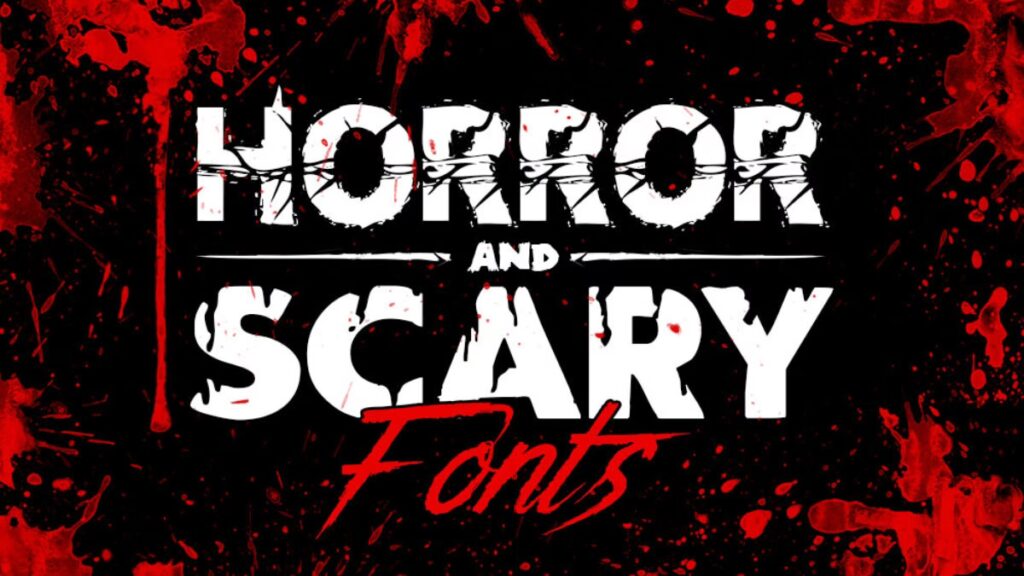
Typografi er et kraftfuldt værktøj i design, og når målet er at vække følelser af frygt, mystik eller ubehag, er valget af skrifttype afgørende. Skræmmende skrifttyper kan forvandle en almindelig plakat til et mareridtbrændstof eller give et logo en dyster, urovækkende kant, der passer perfekt til horror- eller Halloween-temaer. De er et must-have i værktøjskassen for enhver designer eller fotograf, der arbejder med mørke eller uhyggelige koncepter.
Disse skrifttyper er mere end bare bogstaver; de er visuelle elementer, der fortæller en historie, før du overhovedet læser ordene. De kan simulere dryppende blod, gamle, forvitrede inskriptioner, forvredne former, der antyder galskab, eller skarpe, takkede kanter, der skriger fare. At forstå, hvad der gør en skrifttype skræmmende, og hvordan man bedst anvender dem, er nøglen til at skabe virkelig mindeværdige og effektive designs.
Hvad Gør En Skrifttype Skræmmende?
En skræmmende skrifttype er designet til at fremkalde specifikke følelser og associationer relateret til frygt, horror, mystik eller det overnaturlige. Disse følelser opnås gennem forskellige visuelle karakteristika. Ofte ser man skrifttyper med takkede kanter, der ligner revner, kløer eller brudte overflader. Disse uregelmæssigheder skaber en følelse af fare, vold eller forfald.
En anden populær teknik er at simulere fysiske effekter som dryppende væske, mest almindeligt blod eller blæk. Skrifttyper med dryppende effekter er øjeblikkeligt forbundet med horror, kriminalitet eller uhygge. De kan se våde, klistrede og foruroligende ud, hvilket gør dem ideelle til titler eller overskrifter, hvor man ønsker en stærk, grafisk effekt.
Ru teksturer og forvitrede udseender er også effektive. En skrifttype, der ser ud som om den er ridset, plettet, eller ældet, kan give en følelse af historie, forladthed eller dæmonisk besættelse. Disse teksturer tilføjer dybde og realisme til det uhyggelige tema.
Forvredne eller forvrængede bogstavformer kan skabe en følelse af ustabilitet, galskab eller en verden ude af balance. Bogstaver, der ser ud til at smelte, sno sig, ryste eller falde fra hinanden, er dybt urovækkende og kan bruges til at repræsentere mentale forstyrrelser, overnaturlige kræfter eller et generelt tab af virkelighedssans. Kaotiske strøg og uregelmæssige former bidrager til denne fornemmelse af uorden og terror.
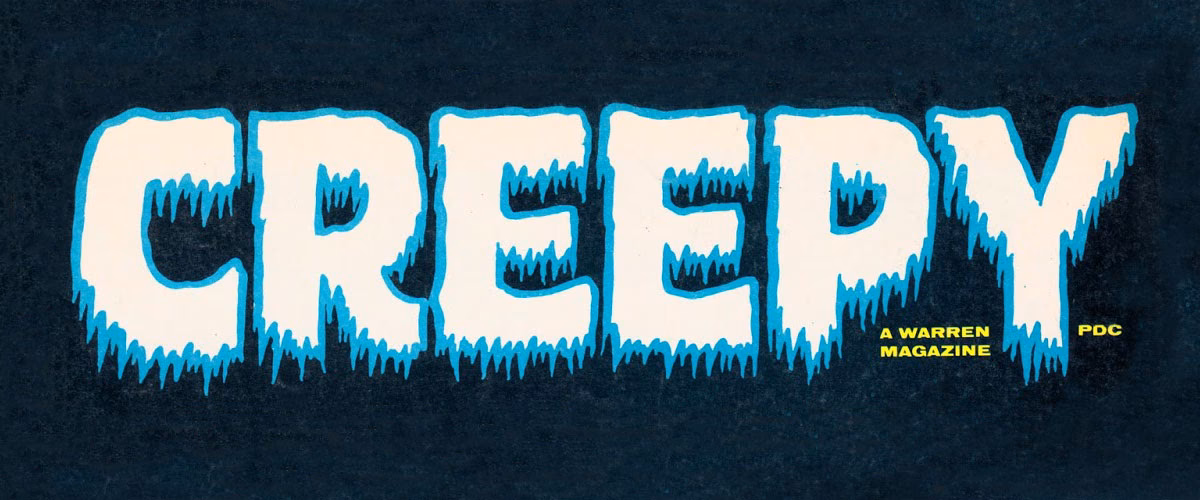
Endelig kan selv enkle, men tunge eller gotiske skrifttyper opfattes som skræmmende, især når de bruges i en passende kontekst. En fed, mørk, gotisk skrifttype kan give en følelse af gammel ondskab, okkultisme eller dysterhed, der fungerer godt til Halloween eller mere traditionelle horror-temaer.
Brug af Skræmmende Skrifttyper i Design og Fotografi
At vælge den rigtige skræmmende skrifttype er kun første skridt. Hvordan du bruger den, er lige så vigtigt for at maksimere effekten. Her er nogle tips til at bruge skræmmende skrifttyper effektivt i dine designs:
- Brug dem sparsomt: Skræmmende skrifttyper er ofte meget dekorative og kan være svære at læse i længere tekstblokke. De fungerer bedst til overskrifter, titler, logoer eller korte sætninger, hvor de kan fange opmærksomheden uden at trætte øjnene. Brug en mere læselig, men passende, skrifttype til brødtekst, hvis nødvendigt.
- Kombiner med passende baggrunde: Mørke, stemningsfulde baggrunde er ideelle til skræmmende skrifttyper. Overvej baggrunde med lav belysning, skygger, tåge, gamle teksturer (træ, mursten, rust) eller billeder, der passer til det uhyggelige tema.
- Tilføj teksturer og effekter: For at forstærke det skræmmende udseende kan du tilføje yderligere grafiske effekter til selve teksten eller dens omgivelser. Dette kan inkludere ridser, pletter, vignetter, lysglimt eller skygger, der får teksten til at se mere integreret ud i designet og mere fysisk tilstedeværende (og skræmmende!).
- Farvevalg er vigtigt: Farver som dyb rød (blod), sort (mørke, død), mørkegrå (skygger, aske) og knoglehvid (spøgelser, knogler) er klassiske valg til skræmmende typografi. Neonfarver som grøn eller lilla kan også bruges til at give et mere overnaturligt eller syret udtryk, især i kombination med mørke baggrunde.
- Tænk på konteksten: Hvilken specifik type horror eller uhygge repræsenterer dit design? En dryppende blodskrifttype passer måske til en slasherfilmplakat, mens en ældgammel, forvitret skrifttype er bedre til et okkult tema. Vælg en skrifttype, hvis stil matcher den specifikke historie eller følelse, du vil formidle.
Populære Stilarter og Eksempler fra Horror
Gennem tiden har visse skrifttypestilarter og endda specifikke skrifttyper opnået ikonisk status inden for horror. De er blevet synonyme med genren og genkendes øjeblikkeligt af fans.
En stil, der ofte ses, er en tung, gotisk-inspireret skrifttype med skarpe, spidse kanter. Denne stil kan føles både gammeldags og truende. Forestil dig en skrifttype, der ser ud som om den er ridset ind i sten eller hugget ud af mørkt træ – den udstråler en følelse af ældgammel ondskab.
En anden stil er den kaotiske, forvrængede skrifttype. Disse ser ud som om de er håndskrevne i panik, eller som om de er påvirket af en overnaturlig kraft. Bogstaverne kan have uregelmæssige størrelser, vinkler eller endda mangle dele. Denne stil er perfekt til at skabe en følelse af ustabilitet, galskab eller dæmonisk indflydelse.
Den dryppende stil, som nævnt tidligere, er også meget populær. Disse skrifttyper ser ud som om de er ved at smelte eller græde blod eller sort blæk. De er utroligt grafiske og vækker øjeblikkeligt associationer til vold, død og uhygge. En skrifttype beskrevet som havende en 'venomous' eller 'dødbringende' udseende falder ofte ind under denne kategori, med elementer der ligner hugtænder eller dryp.
Nogle skrifttyper er blevet berømte på grund af deres brug i ikoniske horrorproduktioner. For eksempel er skrifttypen ITC Serif Gothic ofte forbundet med horror, især efter dens brug i plakater og titler for film som 'Halloween'. Dens skarpe seriffer og tunge vægt giver den et både klassisk og ildevarslende udseende, der har gjort den til et populært valg inden for indie horror og mid-budget film i årtier.
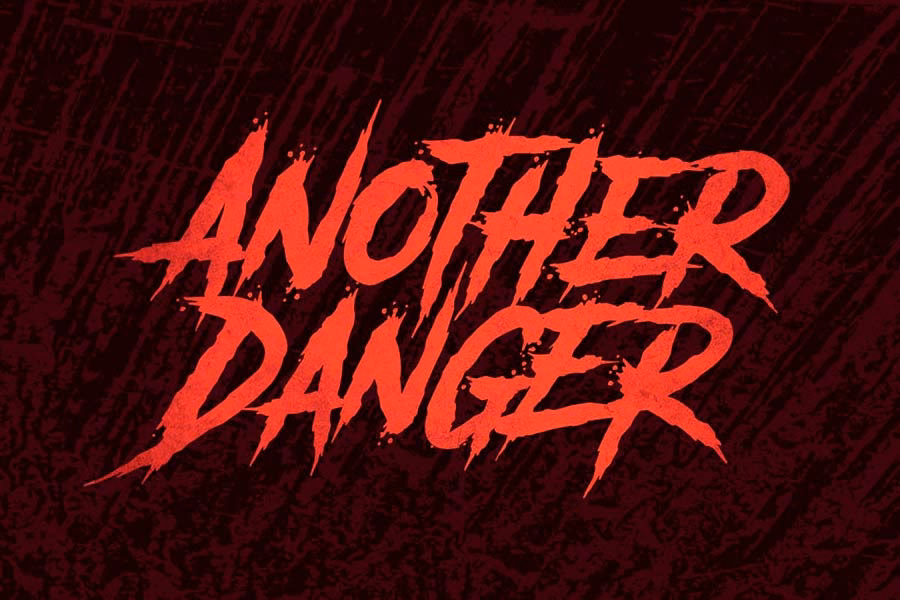
Beguiat er en anden skrifttype, der fik fornyet popularitet takket være successer som TV-serien 'Stranger Things'. Selvom den oprindeligt ikke var designet som en horrorskrifttype, har dens karakteristiske, let afrundede former og seriffer, især i en tung, fed version, vist sig at være utroligt effektive til at skabe en nostalgisk, men samtidig mystisk og uhyggelig stemning. Den er også kendt for at være blevet brugt i mange af Stephen Kings bogudgivelser i 1980'erne, hvilket yderligere cementerede dens forbindelse til genren.
Trajan er en skrifttype, der er nærmest allestedsnærværende i filmplakater på tværs af genrer, men den har også fundet vej til horror. Dens klassiske, romerske udseende kan give en følelse af storslåethed, men i horror bruges den ofte modificeret – med bogstaver i forskellige størrelser, forlængede ascenders og descenders, eller endda med bogstaver der ser ud til at være let fraktureret eller skåret op. Denne manipulation af en ellers 'sikker' skrifttype kan skabe en subtil, men effektiv følelse af noget, der er 'slukket' eller forstyrret.
Udover disse navngivne eksempler findes der utallige andre skrifttyper, der passer til horror og uhyggelige temaer. Disse kan beskrives med termer som 'dæmonisk' (skarpe kanter, aggressivt udseende), 'spøgelsesagtig' (tynd, flagrende eller æterisk, men urovækkende), 'rå og grov' (grunge-effekter, distressed teksturer) eller 'mareridtsagtig' (dybt foruroligende, snoede former).
Selvom kilden nævner en skrifttype ved navn 'Spooky Spell', beskrives den primært ud fra dens stil – inspireret af retro horror tegneserier, håndtegnet, og tilgængelig i en 'crisp' og en 'inked' (blækket, sandsynligvis med tekstur eller let dryp) version. Dette understreger igen vigtigheden af stilen og effekten frem for blot navnet på skrifttypen.
Skræmmende Skrifttypegeneratorer
Hvis du hurtigt vil skabe tekst med et uhyggeligt udseende uden at downloade eller installere specifikke skrifttyper, kan online skrifttypegeneratorer være en god løsning. Disse værktøjer lader dig indtaste din tekst og derefter anvende forskellige horror-relaterede effekter.
Typiske effekter inkluderer dryppende blod, grunge-teksturer, glitch-effekter (der får teksten til at se digitalt forstyrret ud), eller generel forvrængning. Disse generatorer er nyttige til hurtige projekter, sociale medieopslag eller at eksperimentere med forskellige uhyggelige udtryk. Kilden nævner specifikt Font Meme Horror Text Generator, som tilbyder effekter som dryppende blod og grunge. Mens de måske ikke giver den samme fine kontrol som dedikerede designsoftware og skrifttyper, er de en hurtig og nem måde at tilføje et element af uhygge på.
Valg af Den Rette Skræmmende Skrifttype
At vælge den 'mest' skræmmende skrifttype er subjektivt og afhænger helt af den specifikke følelse eller historie, du ønsker at formidle. Der findes ikke én enkelt skrifttype, der er 'den uhyggeligste' for alle situationer. Det handler om at finde den skrifttype, hvis visuelle karakteristika bedst matcher temaet for dit projekt.
Overvej følgende, når du vælger:
| Karakteristik | Visuel Effekt | Ideel Til |
|---|---|---|
| Takkede/Skarpe Kanter | Fare, vold, ødelæggelse | Slasher, dæmonisk, aggressive temaer |
| Dryppende Effekter | Blod, blæk, forfald | Kriminalitet, vampyrer, zombier, kropshorror |
| Ru/Forvitret Tekstur | Gammel, forladt, besat | Spøgelser, forbandelser, okkultisme, post-apokalyptisk |
| Forvrængede Former | Galskab, ustabilitet, overnaturlig indblanding | Psykologisk horror, dæmonisk besiddelse, mareridt |
| Tung/Gotisk Vægt | Dysterhed, ældgammel ondskab, ceremoni | Traditionel horror, gotisk horror, okkultisme |
Tænk over, om du vil have noget åbenlyst og chokerende (som dryppende blod) eller noget mere subtilt og urovækkende (som en let forvrænget eller ældet skrifttype). Skal den se håndlavet og kaotisk ud, eller mere struktureret, men stadig truende?
Ofte Stillede Spørgsmål om Skræmmende Skrifttyper
Hvad er den uhyggeligste skrifttype?
Der findes ikke én enkelt 'uhyggeligste' skrifttype, da det afhænger af den specifikke følelse eller det tema, man ønsker at fremkalde. Skrifttyper med dryppende effekter, takkede kanter, eller kraftig forvrængning opfattes ofte som meget skræmmende, men valget afhænger af konteksten. Skrifttyper som ITC Serif Gothic, Beguiat (brugt i Stranger Things) og modificeret Trajan er kendt fra horrorfilm.
Hvad gør en skrifttype skræmmende?
Skræmmende skrifttyper bruger visuelle elementer som takkede kanter, dryppende effekter, ru teksturer, forvrængede bogstavformer og kaotiske strøg til at fremkalde følelser af frygt, mystik og ubehag. Disse karakteristika bryder med normen for læselighed og orden og skaber en følelse af noget forkert eller truende.
Hvor kan jeg finde skræmmende skrifttyper?
Skræmmende skrifttyper kan findes på forskellige online platforme, der sælger eller tilbyder gratis skrifttyper. Mange designwebsteder har kategorier dedikeret til horror, Halloween eller uhyggelige skrifttyper. Online skrifttypegeneratorer kan også hurtigt skabe tekst med horror-effekter.
Hvordan bruger jeg skræmmende skrifttyper bedst?
Brug skræmmende skrifttyper sparsomt til overskrifter og titler for maksimal effekt. Kombiner dem med mørke, stemningsfulde baggrunde og passende farveskemaer (rød, sort, grå). Overvej at tilføje teksturer eller effekter for at forstærke det uhyggelige udseende. Sørg for, at skrifttypen passer til det specifikke tema for dit design.
Afsluttende Tanker
Skræmmende skrifttyper er et uundværligt redskab for enhver, der arbejder med visuel kommunikation inden for horror, Halloween eller andre uhyggelige temaer. De har evnen til øjeblikkeligt at sætte stemningen og fange beskuerens opmærksomhed på en måde, som almindelig tekst sjældent kan. Ved at forstå de forskellige karakteristika, der gør en skrifttype skræmmende – fra dryppende effekter og takkede kanter til forvrængede former og ru teksturer – kan du vælge præcis den rigtige typografi til at bringe dine mest skræmmende visioner til live. Uanset om du bruger en klassiker fra horrorfilmhistorien, en specialdesignet skrifttype eller en hurtig generator, er det vigtigste at vælge en skrifttype, der resonerer med den følelse, du ønsker at skabe, og bruge den klogt inden for dit design. Gå på opdagelse i den mørke side af typografien, og lad dine designs give folk kuldegysninger!